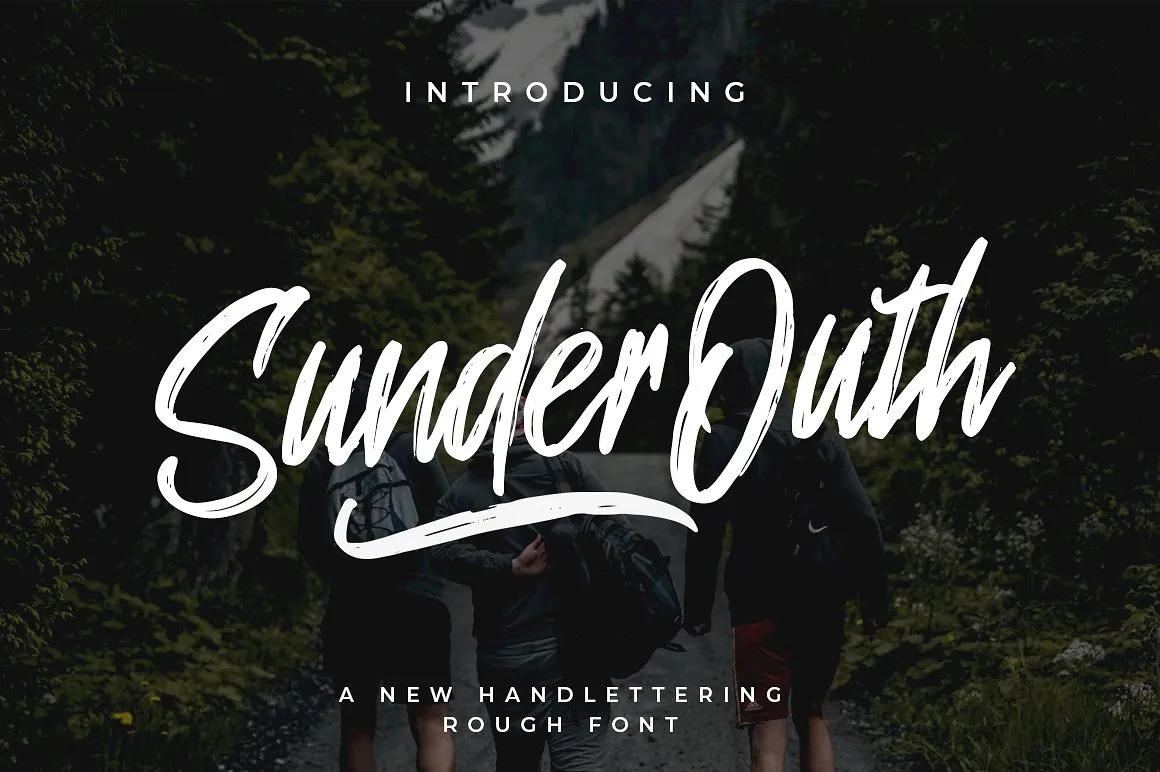
Sunder Outh Brush Font – Fonte Grátis
Sunder Outh Brush Font
A ‘Sunder Outh Brush Font’ é uma nova seleção para quem gosta de trabalhar com letra cursiva a mão. Esta fonte brush está perfeitamente ajustada para destacar seu texto, criando um efeito moderno e inovador em qualquer projeto. Ela foi projetada por Indotitas e compartilhada pela designer zziplex. Com sua aparência rústica e estilo claro, a ‘Sunder Outh Brush Font’ é perfeita para diversos usos como logomarcas, cartazes, selos, embalagens, materiais promocionais ou até mesmo na customização de roupas. Suavemente fluida, esta fonte será uma excelente adição para qualquer projeto gráfico. E a sua versatilidade também se estende para o design em papel, como cartazes e convites, tornando-a perfeita para uso em diversos segmentos do mercado. Ainda não experimentou a ‘Sunder Outh Brush Font’? Agora é a oportunidade de explorar uma fonte que vai transformar sua atuação gráfica. Com o seu design limpo e forte, esta brush font promete dar um toque único e moderno a qualquer projeto que você criar.